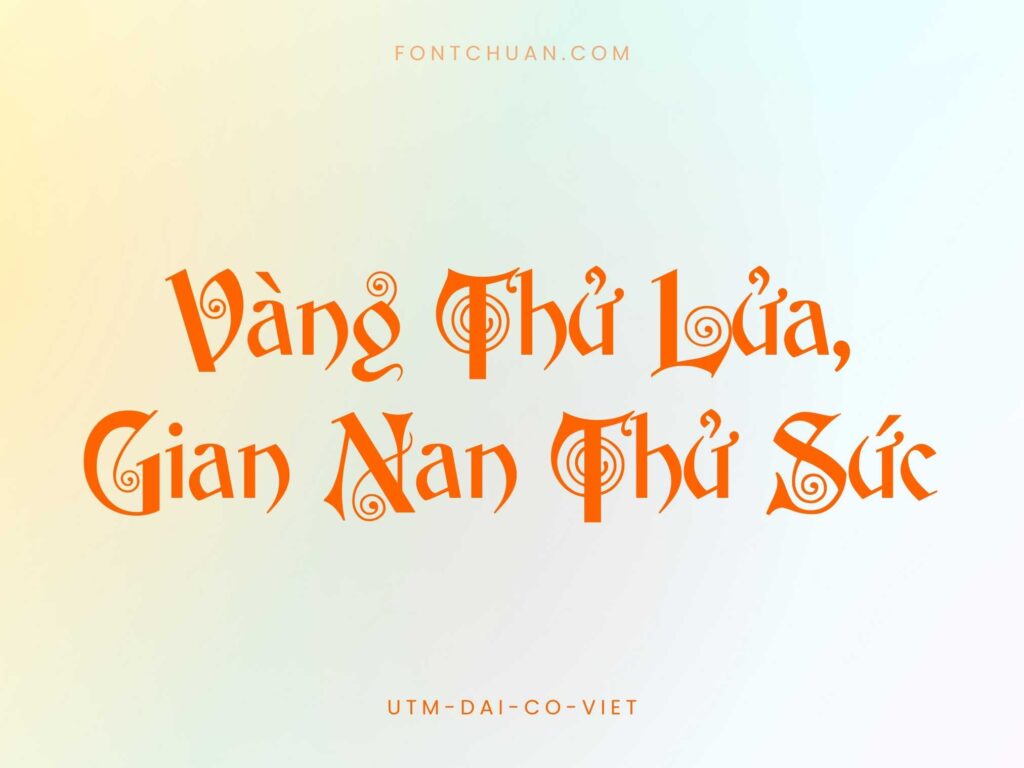
Font UTM Đại Cồ Việt Việt Hóa là một Font chữ cổ trang, lấy cảm hứng từ những nét chữ truyền thống của Việt Nam. Font gốc có tên là Đại Cồ Việt, với các nét chữ cứng cáp, uốn lượn tinh tế, font này phù hợp với các thiết kế mang tính lịch sử, truyền thống và văn hóa.
Font này đã được Việt hóa để hỗ trợ đầy đủ tiếng Việt bởi Thiên Minh, ngoài ra còn hỗ trợ nhiều ngôn ngữ khác. Thành viên của Font Chuẩn đã sưu tầm và chọn lọc font này nhằm đáp ứng nhu cầu của người dùng trong thiết kế và ứng dụng thực tế. Font có đặc điểm nổi bật với đường nét sắc sảo, phù hợp với các dự án như thiết kế poster, ấn phẩm văn hóa, bìa sách, và nhiều lĩnh vực khác.